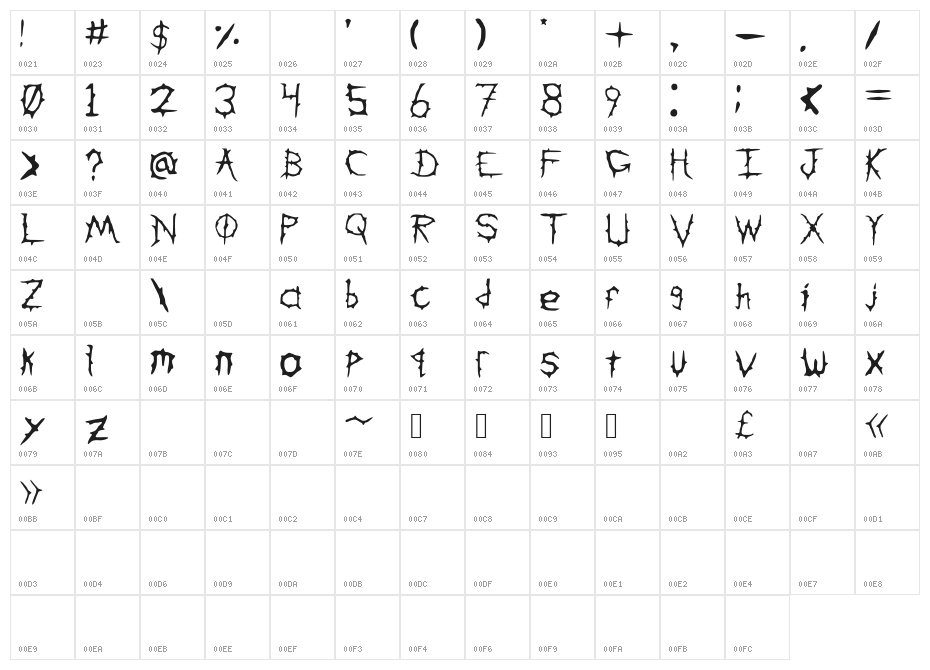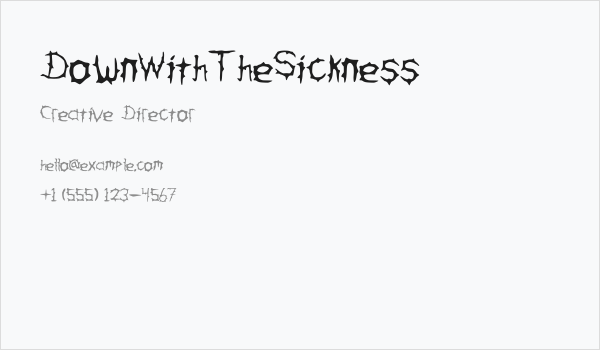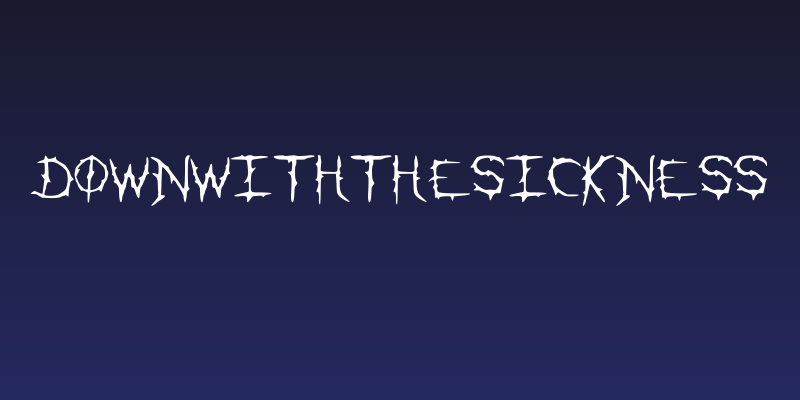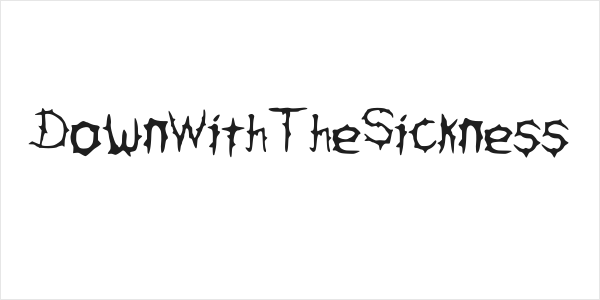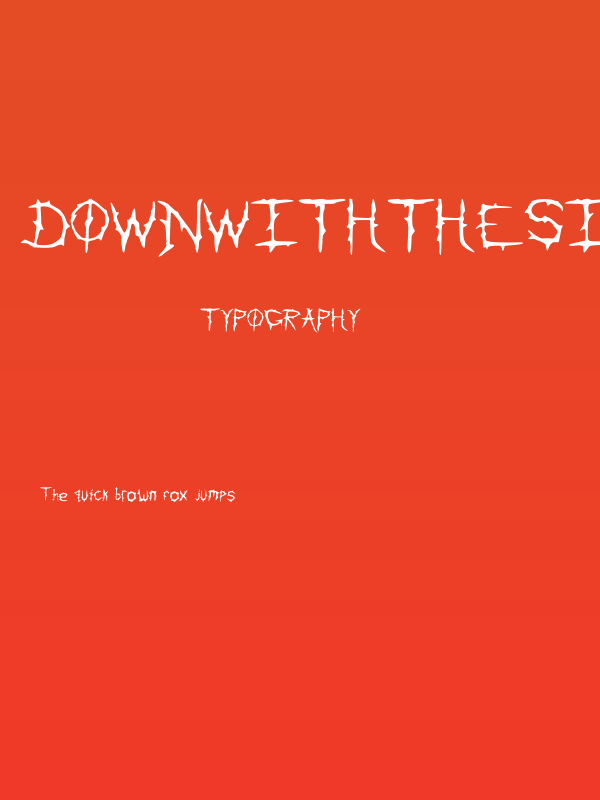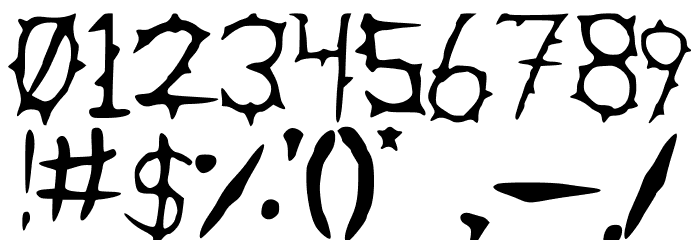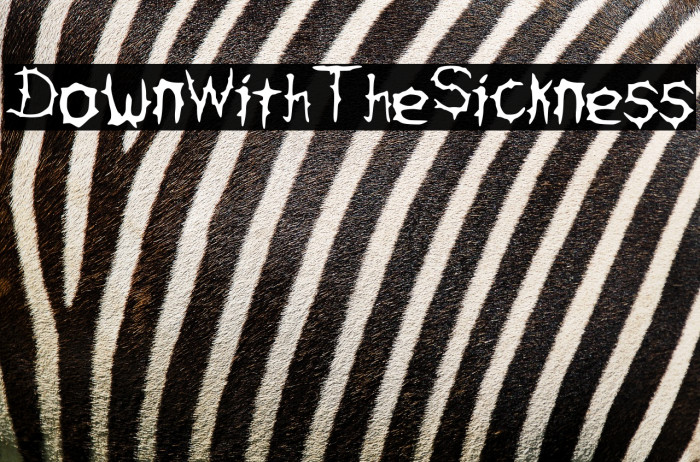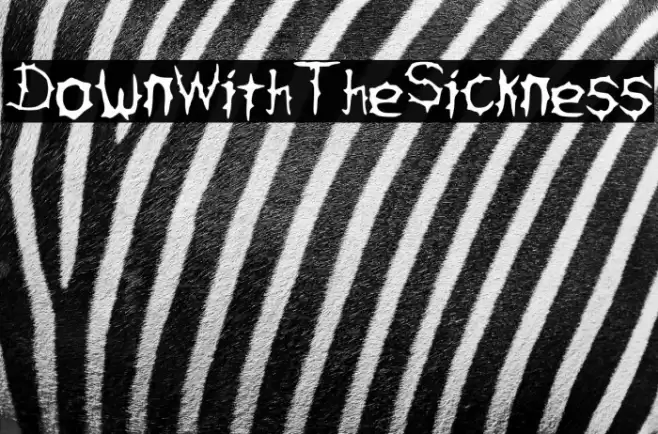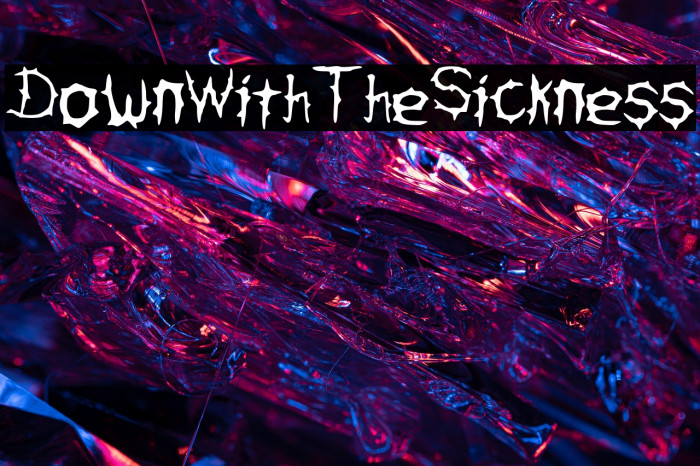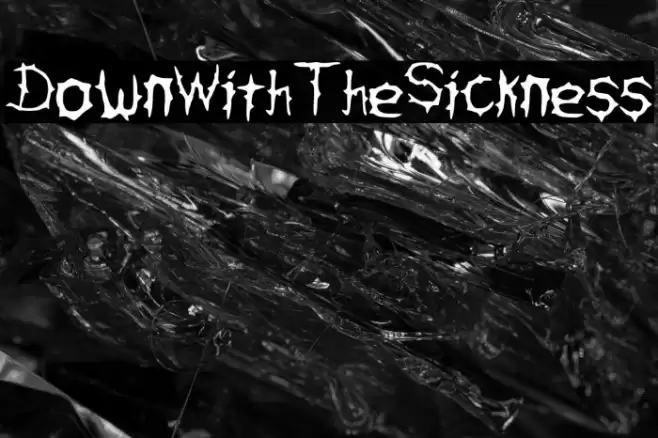
DownWithTheSickness Font
✎ Messy
| Proiecte propuse | Ideal for horror-themed designs, music album covers, edgy posters, or any project requiring a bold, rebellious look. |